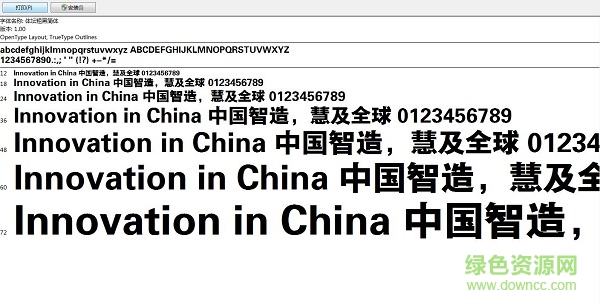
ttchhjt 字體
ttchhjt gb10字體又叫體壇粗黑簡體,字體密度高,字形干凈大氣,具有現(xiàn)代感,可以滿足各種書刊雜志的標題使用要求。有需要者歡迎免費下載!
ttchhjt字體特點
字形結(jié)構(gòu)比較傳統(tǒng),中宮緊湊,筆畫粗重堅實,高品質(zhì)字體推薦,廣泛應(yīng)用于宣傳、廣告、商標、標語、黑板報、企業(yè)名稱、會場布置、展覽會等!